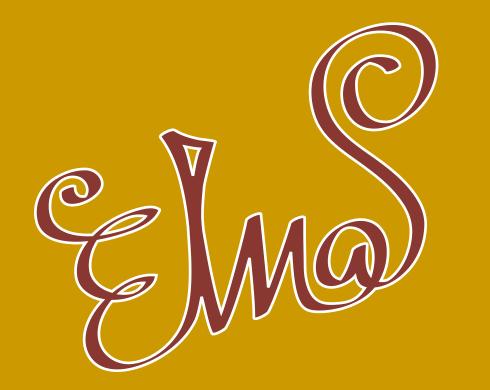
Elmas is een muziekgroep bestaande uit zes mensen die met elkaar de liefde delen voor klezmer- en balkanmuziek. Voor deze groep ontwierp Sander Neijnens een logo dat gebaseerd is op de diverse instrumenten. In de lettervormen zitten verwijzingen naar de viool, sopraansax, accordeon, grote trom en soesafoon. Hiernaast een balpenschets, enkele digitale schetsen en de definitieve versie van het logo.